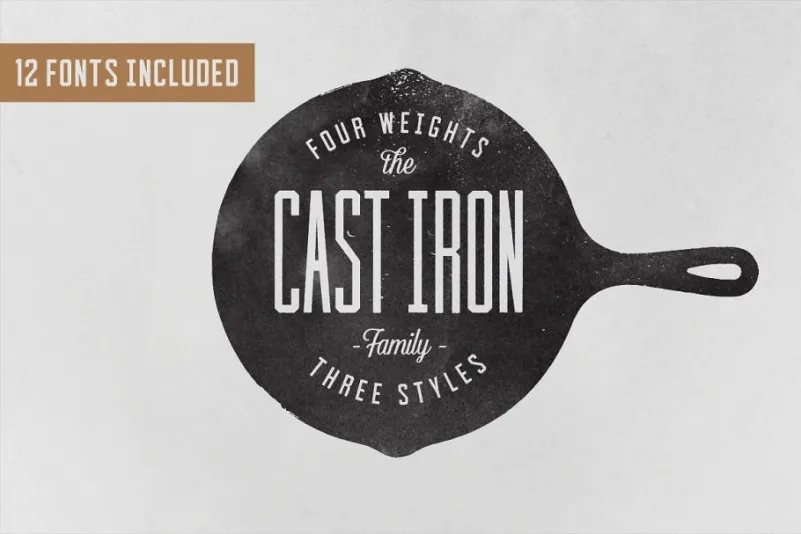
Cast Iron Display Font – Download Grátis
A fonte ‘Cast Iron Display’ é uma elegante escolha para estilos futuristas e tecnológicos. Ela foi criada pelo Hustle Supply Co com alta contração e contraste, tornando-a perfeitamente adequada para aplicações em logomarcas, cartões de convite, etiquetas, revistas, livros e cartões de aniversário ou casamento. Sua textura forte também a faz excelente para pacotes, moda e maquiagem, bem como papelaria, literatura, selos, propaganda e outros formatos formais. É perfeita para qualquer aplicação que deseja transmitir um estilo sólido e moderno com seu design único.